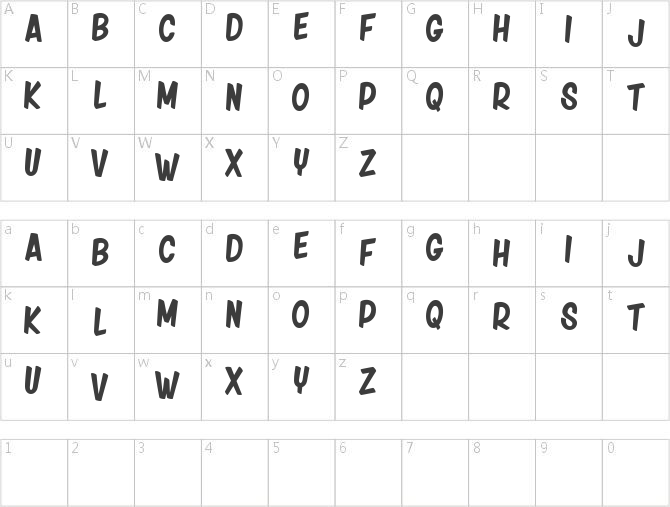
字體名稱: friday
friday night
friday night字體字庫是一款讓人賞心悅目、百看不厭的英文字體,適合各類廣告和產(chǎn)品包裝設(shè)計(jì)應(yīng)用,字體大小0.04MB,格式為ttf字體,上傳用戶是誠(chéng)澤永信,作者/版權(quán)方為未知